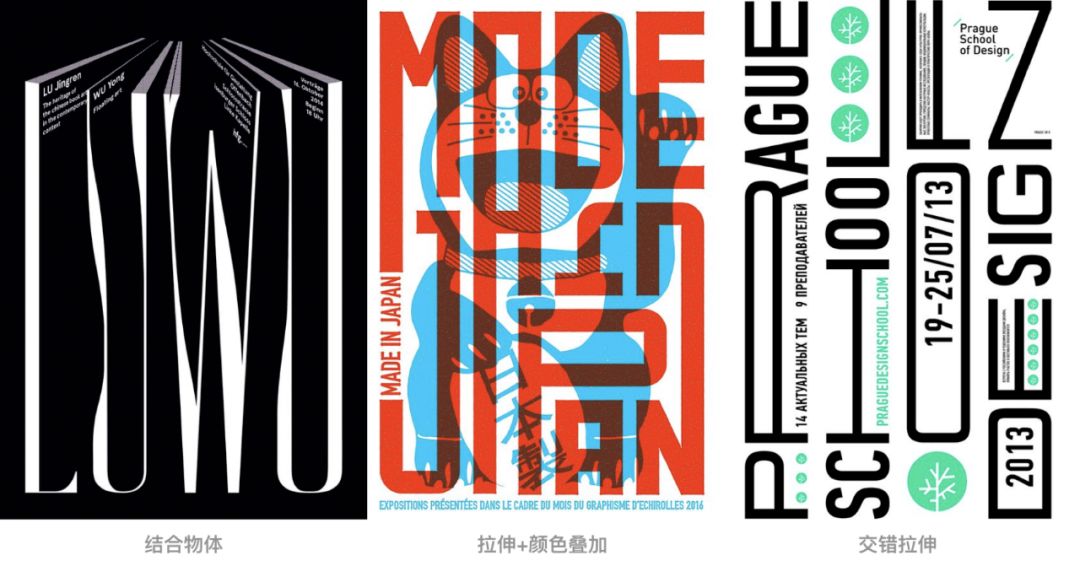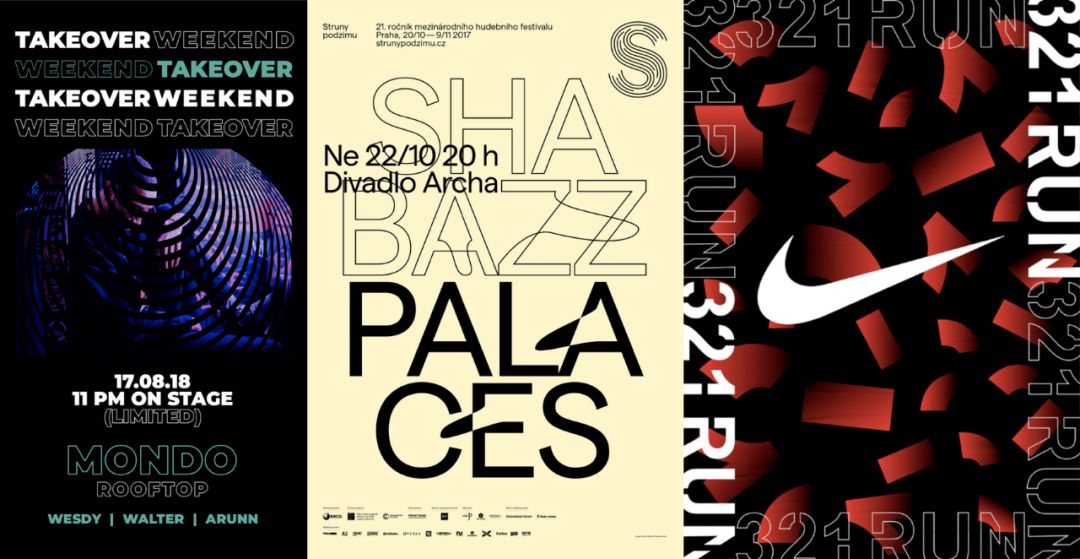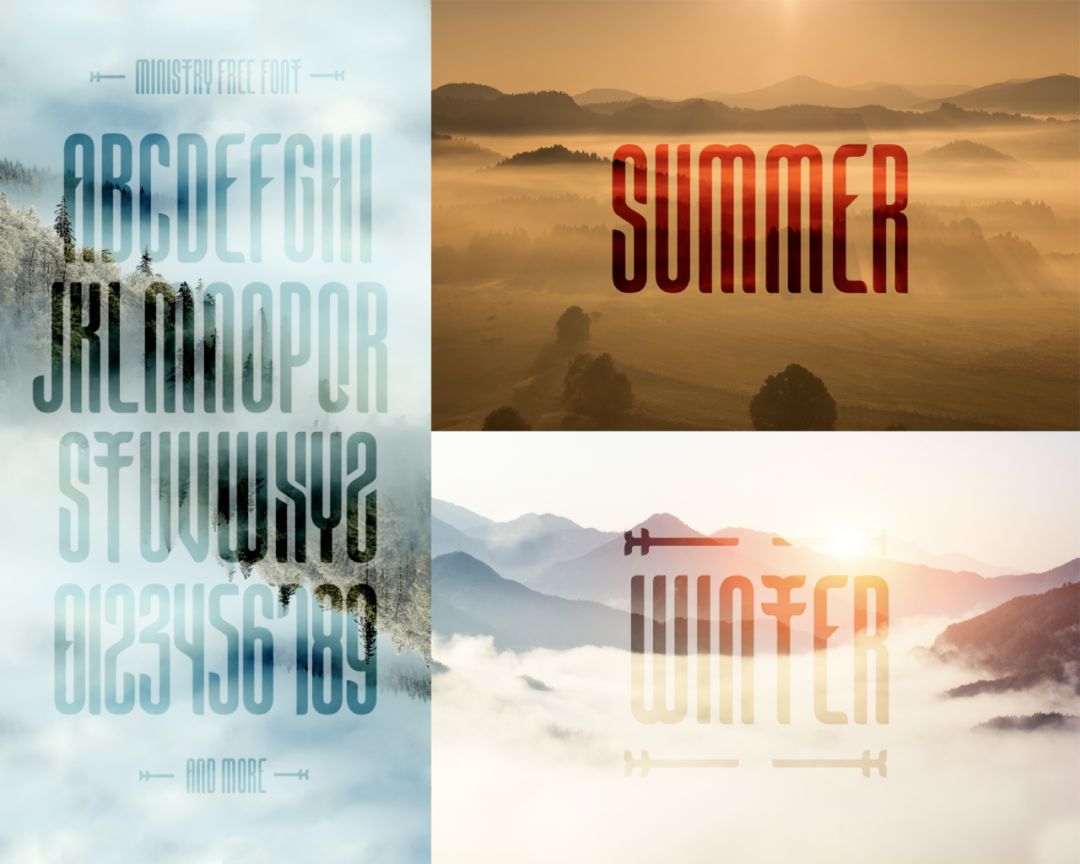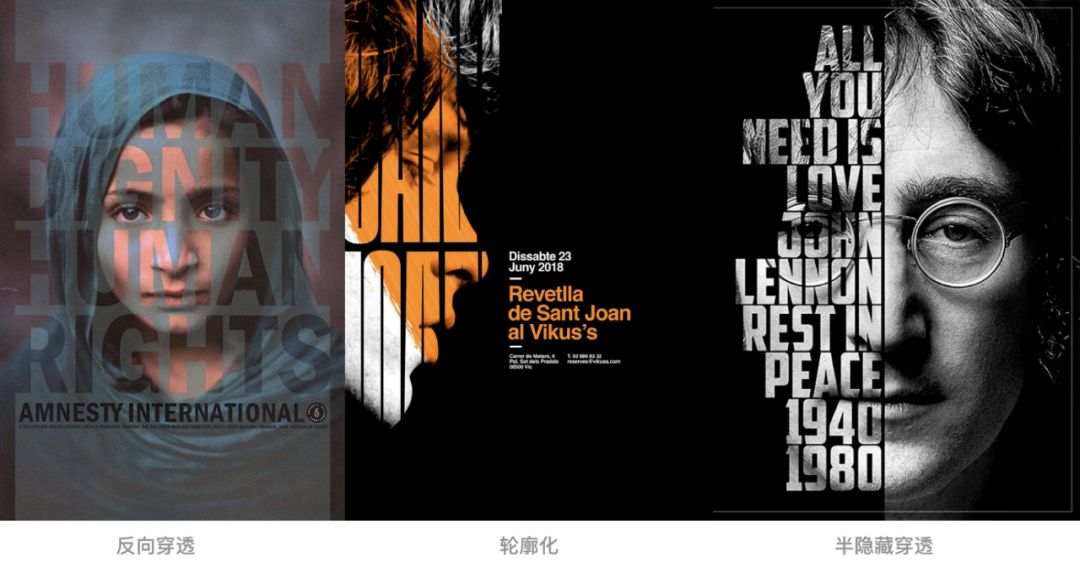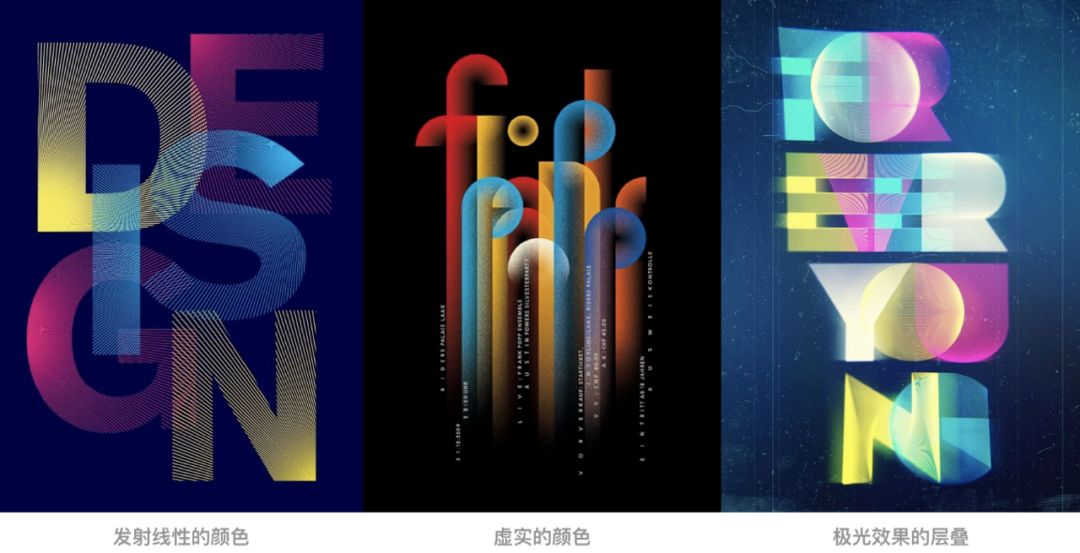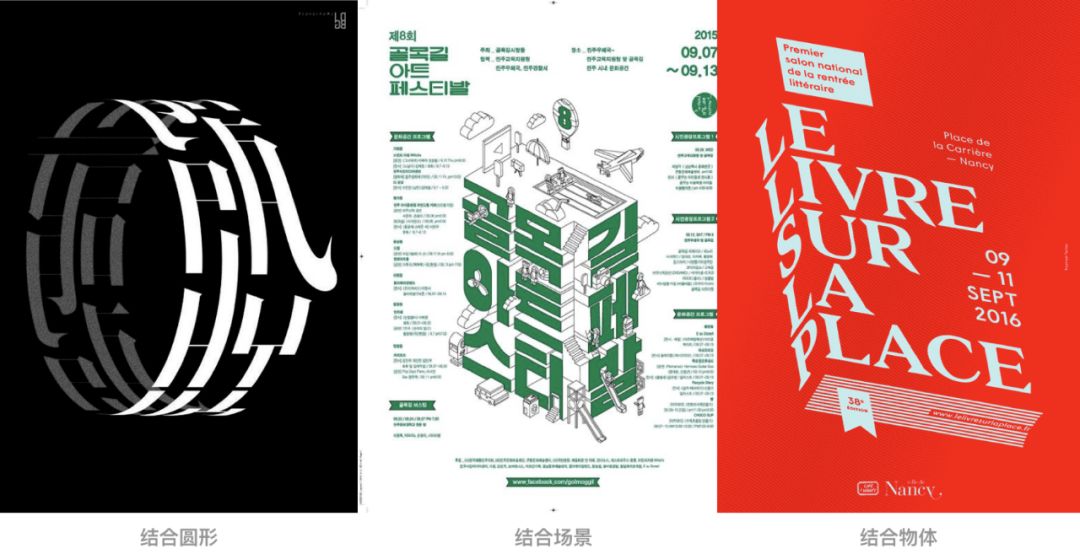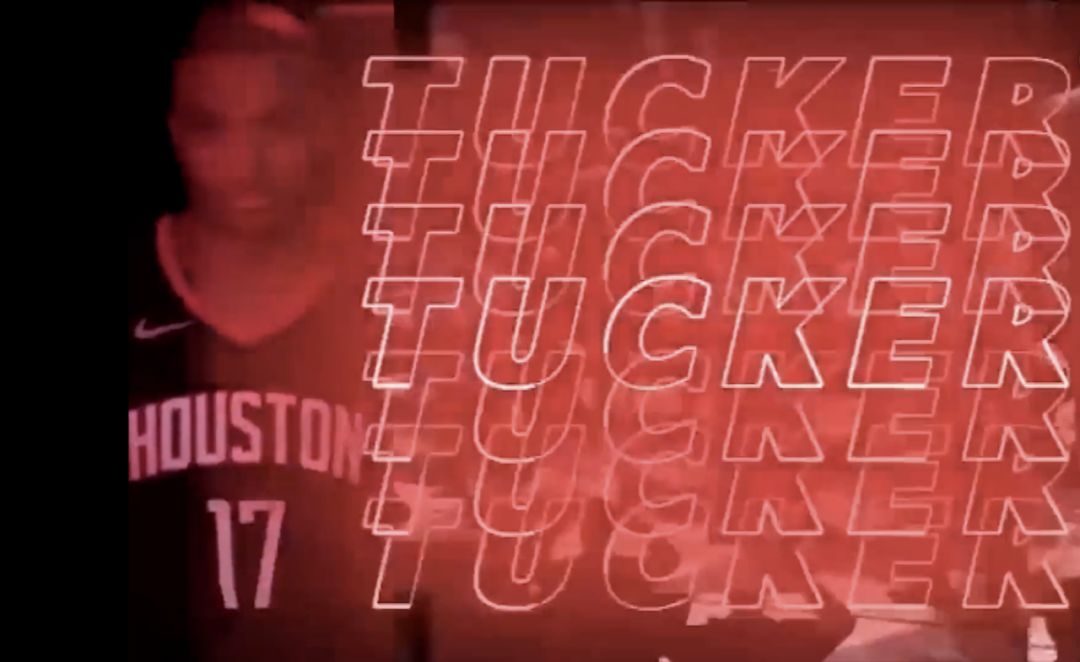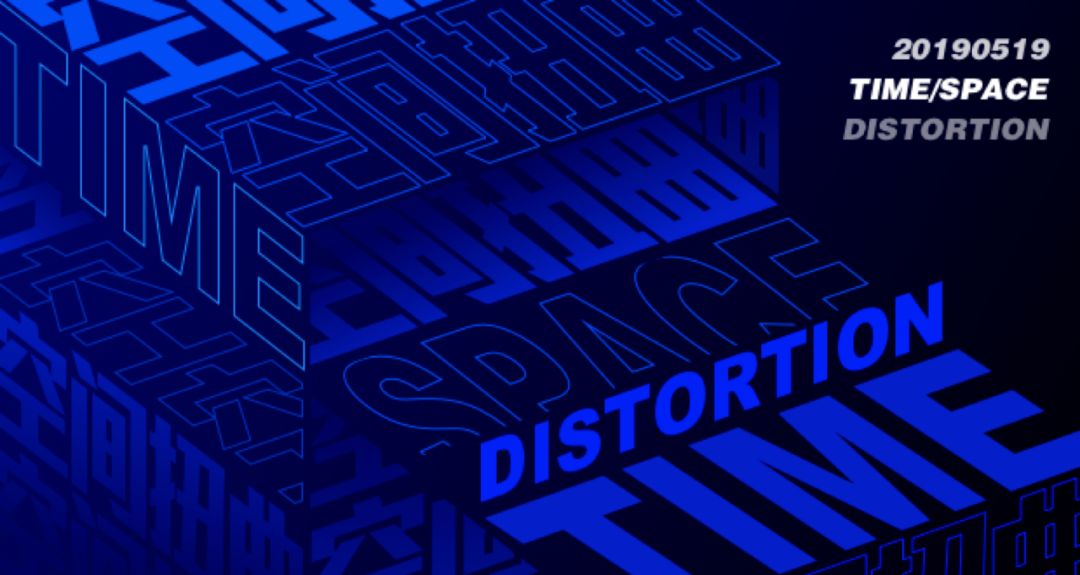
如何提升文字设计感,提升文字设计感的10种方式
我们在设计中除了接触到图形,还需要了解文字的设计。特别的文字设计或者排版可以使整体的画面效果更加有氛围,甚至超过图形表达的感受,更加直观的表达出内容的主旨。
文字的设计方式有很多种,例如通过字体变形,结构重组等方式来让文字变得更加特别,但往往会让我们耗费比较多的时间。
因此我一直在思考有没有一些方法,既简单又高效的设计方式来提高文字的设计感。在浏览国外的一些设计网站的过程中,做了一下文字设计形式方面的收集,并整理出十种我认为具有代表性的文字设计形式。另外还参考这些设计方式,使用中文字体进行了一些尝试。
一、拉伸的文字
拉伸的处理手法,让文字更具有张力,整体氛围更具标题感和图形化,但依然保留这文字该有但识别度。常见于纯文字排版的海报,既满足阅读需要,同时具有设计感。
拉伸与文字本身的字形、字体有着很大程度的关联,并不是所有的文字都适合拉伸,例如下面的案例
不同字体对比
从方案尝试中看出,左边字体在进行拉伸之后,文字本身的结构会遭到破坏,而右边的效果则较为可以接受。因此在设计的过程中尽量选择可适用于拉伸的字体,另外在拉伸的过程中需要对细节重新处理,使字体保留原有字体的细节美感。
不同字形的对比
从下面案例中对比,O在进行上下拉伸的时候效果比较好,而左右拉伸的时候会失去字体本身的美感,而Y在上下左右拉伸后整体视觉效果都相对平衡。
细节处理对比
优化字体线条的细节可以使得整体文字更加规整、方正(右边)。而未进行细节的设计则会显得笔画参差不齐(左边)。
传统与现代对比
传统的字体拉伸后(如下图中间的字体),字体本身的韵味就失去了,因此不建议对于一些较为传统的字体进行拉伸设计。
设计尝试
中文字的笔画比较多样性,因此在细节的设计上比英文来得更加复杂,在处理“撇、捺、点、折、弯、勾”时需要保持原本的笔画结构性。
拓展案例
结合实际要表达的内容,使用拉伸的设计手法,例如结合物体,叠加颜色或者交错拉伸等。
二、虚实结合文字
虚实结合即为线面/阴阳的设计手法,通过虚实的处理,可以突出一组或一段文字中的重点信息。在一些强调主次的设计中,可以尝试这种方式来做区分,线面结合的处理手法让原有都是面的字体多了一些的透气感和空间感。
虚实处理的方法需要考虑本身字体的粗细,过分纤细的字体效果可能并不明显,
尝试对比:
从对比中,发现粗体相比于细体来得更加直接更容易出效果,对比明确。
中文字体的尝试
从尝试中来看,与上面中的结论较为一致,较细的字体使用虚实结合效果并不理想。对于书法体的应用,更多需要考虑字体的收边效果是否工整,收边过碎,会影响在描边之后的细节美感。
设计尝试
三、递进渐变的文字
通过递增或者递减的设计手法,让原本简单重复的文字元素,变得更加具有层次感和节奏感,让文字的生命力变得更加丰富多样。
在设计的过程中需要提前规范好各个之间的差异关系及变化的效果过程。按照一定的数值倍数差异比进行变化。
不同方式的尝试对比:
在尝试的时候发现,粗细变化的模式可能更多会依赖于字体本身的模式。
中文字体的尝试
中文在使用递进渐变的方式中需要考虑整体文字的结构感和块状感,由于字形较为复杂,整体视觉效果会过于零碎。
四、扩展变化的文字
与递进渐变接近但却又差别的文字设计形式。扩展变化的文字具有张力的同时具有一定的速度感和发射性,就像向四周展开的波纹效果,具有延续性。
按文字的行高或者字宽作为基础值,按一定的比例,对文字进行破形切割处理,上下左右进行扩展发散。
比例值示意效果:
中文字体的尝试
外观的完整度还算可以,但由于中文本身自有的特性(笔画较为丰富多样),因此在扩展层次的数量上需要进行一定的控制,不宜过多,以短语或标题使用较好,避免过于形式而导致文字识别性降低。
设计尝试
五、底纹的文字
文字作为纹理出现在画面中,区别于图形化的纹理。既有图形感,同时可以辅助传达一定的信息和态度。
在字体的选择上尽量适用字形较为简洁的字体,避免影响前景内容的展示。设计上可以结合其他的设计形式,例如虚实结合/拉伸变形/扩展变化等方式,提升画面的丰富程度。
中文字体的尝试
常规的中文字体,整体效果还算不错。但结合中国书法字作为底纹,可以让整体的设计更具有不同于英文的设计感,整体效果更具有力量感,因此建议在设计中文底纹的时候可以大胆尝试中文书法字。
六、穿透的文字
通过叠加的方式,让原本简单的文字和背景产生了融合。既提升了背景的层次感,又让文字变得具有设计感。
粗细的字体会产生不一样的视觉感受,较细的字体会产生若隐若现的视觉效果,文字的识别性会稍弱,较粗的字体识别度基本上没有太大问题,因此在设计的过程中可以结合实际的情况选择不同粗细的文字。
粗细对比尝试
穿透的文字设计,对于打造设计的大片感具有很突出的视觉效果。例如漫威的电影片头设计
中文字体的尝试
结合不同的语意使用不同的字体,再结合穿透的设计方式,使画面具有中文的文艺感。
拓展案例
结合实际的内容设计,穿透文字的玩法还可以拓展出更多不一样的设计,例如下面这些例子。
七、扭动的文字
扭动的设计,让文字具有曲线的动态感,提升了文字的装饰性。不同曲线的动态变化,赋予文字不同的律动感。变形的文字并未影响到文字该有的识别性和阅读感,却具有了设计感。
如下面的三个案例,曲率的差别,赋予文字不同的动态规则,具有了不同的视觉感知,有时柔美,有时却具有速度感。因此在设计的时候,可根据具体的内容设计不同的扭动趋势。
中文字体的尝试
对比可见较细的字体使用扭动的设计,效果并不理想。由于中文笔画的差异点,经过扭动之后整体外形较为不规整,而粗体的效果则较为规整,动态曲线趋势也较为明显。
设计尝试
扭动+虚实+底纹的效果。
拓展案例
更高级的设计手法是利用自然环境的介质结合文字,起到扭曲的视觉效果。
八、立体层叠的文字
与扩展变化有异曲同工之妙,文字通过按一定的角度和位移间隔,由二维向三维的视觉效果进行变化,让文字更加多变化、重量感、层次感。
立体层叠的设计对于字体本身具有一定的要求,较为纤细的字体出来的效果并不理想,
不同的字体尝试
从对比中看出,细体或较细的衬线字体,层叠后会出现衔接不上或视觉黑点的情况(如下面左图和右图)。因此设计时建议使用粗体,并且整体笔画较为平均的字体(中间的图)。
中文字体的尝试
虽然具有了层次感和空间感,但也会让整体变得更加复杂,因此需要根据文字但多少情况进行使用。
拓展案例
立体层叠还不止单向的设计,例如可以进行轨迹变化,向外扩展层叠,或是增加一些颜色渐变来丰富整体的设计。
九、颜色叠加的文字
文字通过错位,叠加,颜色变化,透明度变化,切割等方式的设计之后,具有故障的视觉偏差感知。整体视觉感知类似双重曝光的照片,文字具有丰富的层次感。
颜色叠加的效果,对于颜色的选择极为重要,两个颜色交错之间的颜色可以为过度色或者互补色。
细体的效果并不理想(如上图左边第一个),建议设计的过程中使用较粗的字体,另外在使用的过程中需要考虑文字的识别度(如右边的效果),重叠之后文字的识别度或多或是会受到影响。
中文字体的尝试
由于中文字比英文复杂,因此使用中文字在设计的时候,可以寻找一些共笔的地方进行重叠(如下图左边的设计),利用字体笔画粗细一致的情况下,进行了边与边的重叠。另外在设计的过程中建议加大字距离,这样可以避免不同文字的重叠,产生过度复杂的效果,影响文字的识别性(如下图最右边的设计)。
拓展案例
在简单的叠色之外,结合不同质感和肌理,可以让整个文字更具有不一样的视觉感受。
十、立体空间的文字
文字按照立方几何结构进行排版,通过颜色差异,阴阳,线面等方式设计处理后形成空间感和立体感。相比于平面排列的文字更具有空间感和层次感,提升整体画面的设计感。
设计尝试
使用空间错位结合虚实的设计,让简单重复的文字变得具有空间感和立体感。
拓展案例
除了常规的空间打造,甚至可以融入到场景中或者结合物体本身的设计。
以上设计风格,常常会在一些运动品牌的设计中看到,如下:
Nike的设计中应到的文字,也会结合这些方式,来丰富和提高整体的设计感。
火箭队出场片头的字体应用,线形字体叠加渐变的效果,具有层次感又有未来感。
阿迪达斯的广告
Converse的广告
Under Armour的广告
除了一些品牌的设计,音乐唱片的封面也有应用到这些类型的设计手法。
我们除了在一些常规的媒介上会看到相关的文字设计,在这两年的耐克或阿迪达斯的鞋子设计中,也会加入文字元素的设计,甚至球员会直接在鞋子上直接写上文字。
其他更多—文字设计的拓展叠加
文字的设计已经成为一种新的设计趋势,结合实际需要表达的想法,对于设计手法进行活学活用是做出好设计的关键。当然对于基础手法的掌握才可能做到举一反三的设计思考。在实际设计的过程中,我们往往不会是单独使用某一种方式,而是对不同的设计手法进行重组再设计,或者使用2-3中方式叠加设计来打造整体的画面效果。如下:
最后
在这十种基础的文字设计中,通过结合发散可以迸发出远远不止于十种的创意设计。本次收集总结除了自身学习提高之外,希望可以起到抛砖引玉的作用,激发设计师对于文字的设计思考。